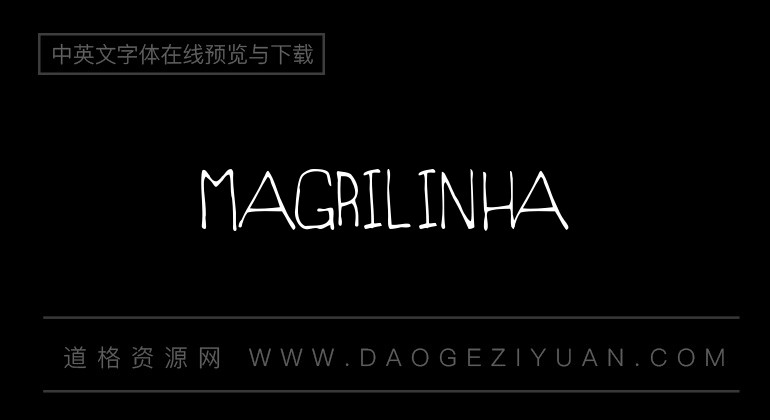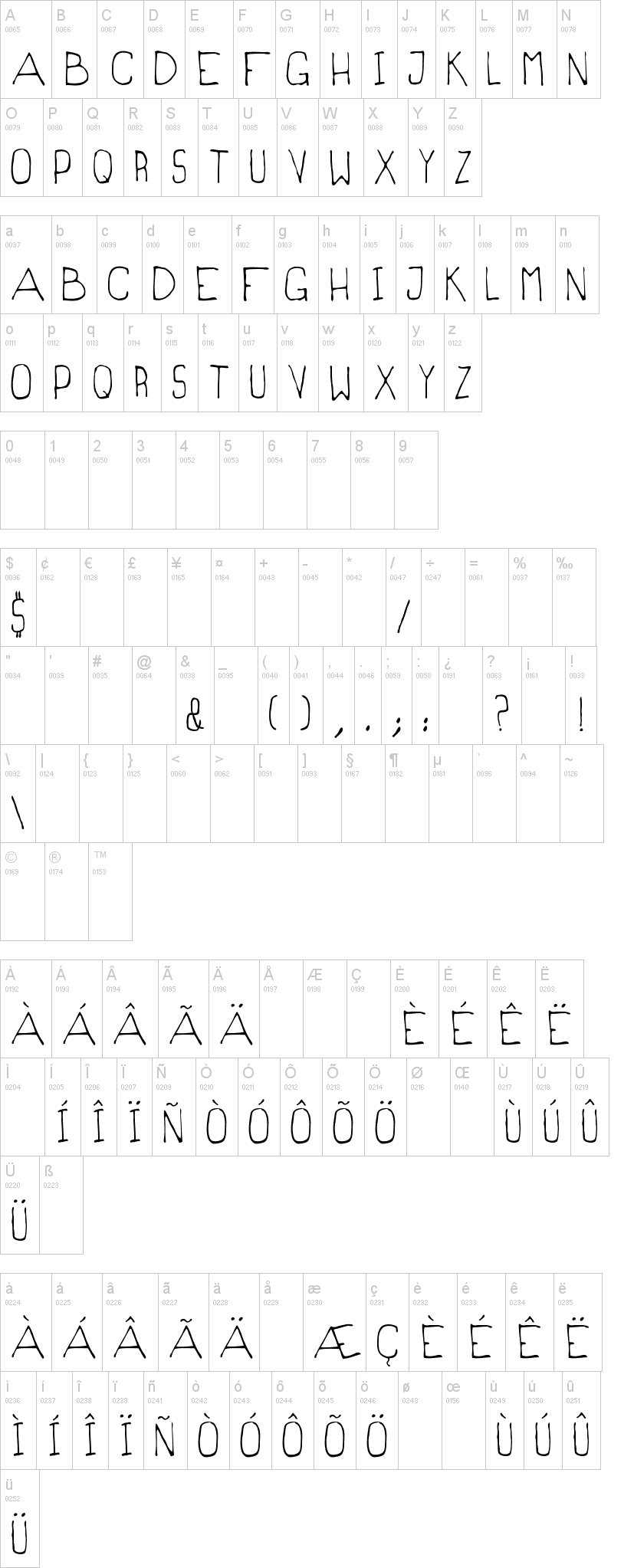
Magrilinha 是一款拉丁文字体,由葡萄牙设计师 Joana Correia 创作。它的特点是细节丰富、曲线柔和,表现出浓浓的传统气息。它的字体风格灵感来自于葡萄牙传统的建筑、民间绘画和服装,以及葡萄牙语的音乐和文化。Magrilinha 字体让人想起了葡萄牙的温馨和活泼,可以应用于多种场景,如商业广告和字体设计等。内容介绍
Magrilinha是一款非常不错的手写艺术字体,具有很好的视觉感,适合于文化类的宣传设计、商业类品牌的广告和产品包装设计以及个性化文字排版等较多场景。